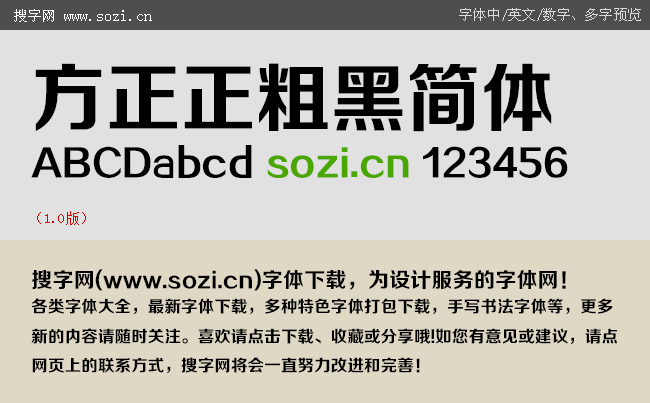
方正正粗黑簡體
搜字網提供一款方正正粗黑簡體中文藝術字體下載,方正正黑系列字體是專為企業(yè)視覺識別系統(tǒng)設計的專用字體,字體字面擴張,重心高,筆畫處理有對稱的規(guī)律性、鏡像感,效似綜藝。在基礎上結合黑體筆形及結構特征,使其更富于靈動變化,端莊大氣又不失簡潔時尚的美感,適用于企業(yè)視覺識別系統(tǒng)的設計字體,以及版式設計中標題用字、標志設計用字等。